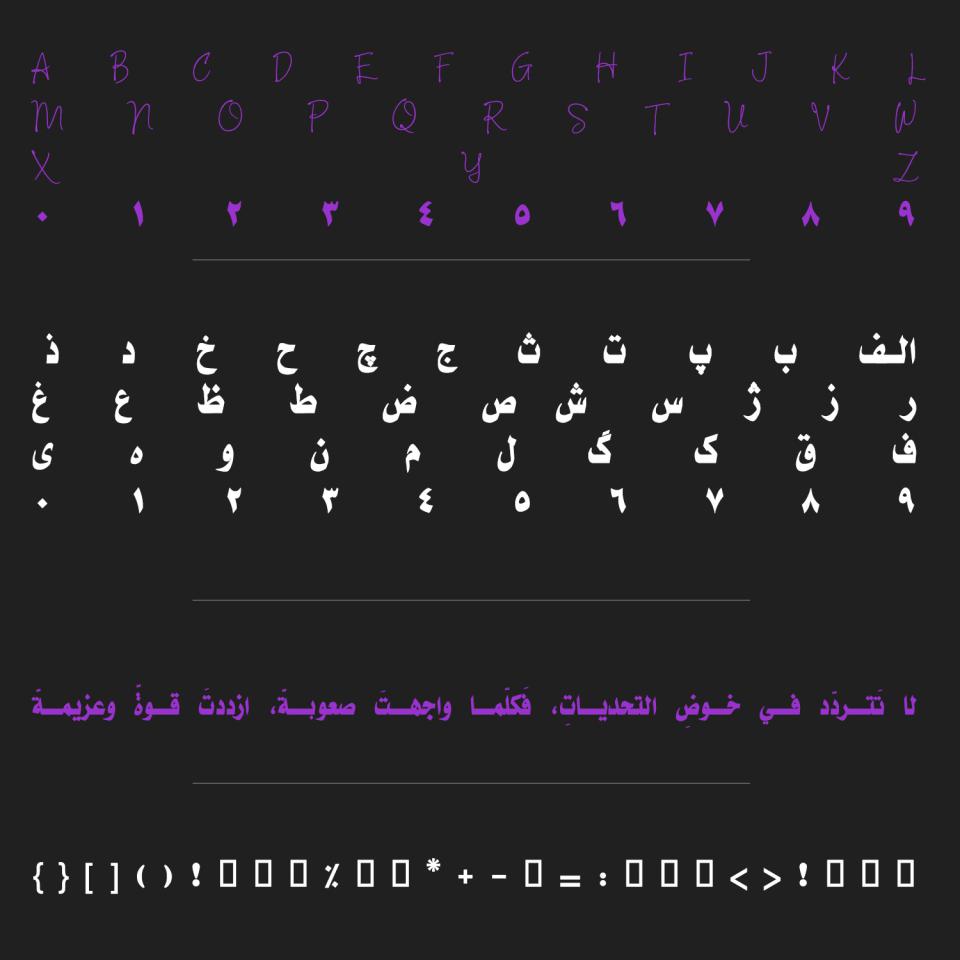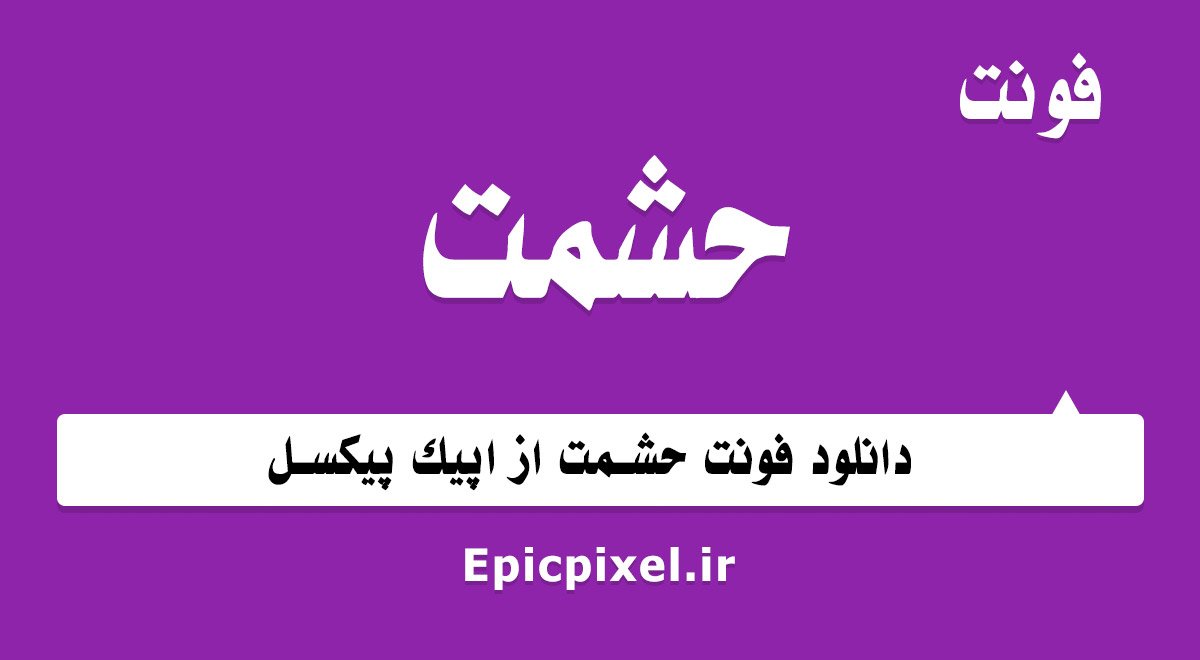
2 فونت حشمت فارسی Heshmat
فونت حشمت، با استایلی زمخت و درشت، انتخابی ایده آل برای طراحی هایی است که نیازمند جلوه ای قدرتمند و متمایز هستند. این فونت رایگان، با ارائه حروفی با ضخامت زیاد و خطوطی قاطع، حس استحکام و پایداری را به مخاطب القا می کند. اگر به دنبال فونتی هستید که در نگاه اول توجه را جلب کند و پیامی قوی را منتقل سازد، حشمت گزینه ای مناسب است.
این فونت به خوبی در طراحی لوگو، عناوین، پوسترهای تبلیغاتی و بسته بندی محصولات کاربرد دارد. فرض کنید می خواهید برای یک برند ورزشی یا یک محصول صنعتی، هویتی بصری خلق کنید؛ فونت حشمت با ساختار خاص خود، به این طراحی ها روح می بخشد. با وجود ظاهر زمخت، این فونت خوانایی مناسبی در اندازه های بزرگ دارد و به خوبی در پروژه های چاپی و دیجیتال نمایش داده می شود.
البته باید به این نکته هم توجه داشت که به دلیل ضخامت زیاد، استفاده از آن در متون طولانی و اندازه های بسیار کوچک توصیه نمی شود، زیرا ممکن است خوانایی آن کاهش یابد. با این حال، اگر به دنبال ایجاد کنتراست و تاکید بر کلمات کلیدی در طراحی های خود هستید، فونت حشمت می تواند به عنوان یک ابزار قدرتمند مورد استفاده قرار گیرد. این فونت با ارائه فرمت های مختلف، سازگاری بالایی با نرم افزارهای طراحی گوناگون دارد و به راحتی می توانید آن را در پروژه های خود به کار ببرید. به طور خلاصه، اگر به دنبال فونتی رایگان با استایلی خاص و قدرتمند هستید، فونت حشمت انتخابی ارزشمند برای شماست.